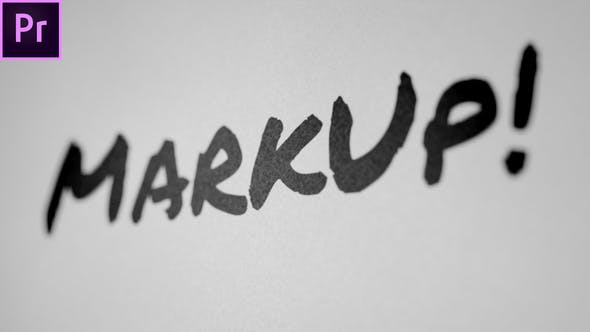
Videohive – MarkUp – Animated Typeface for Premiere – 30833779
هذا محرف متحرك يمكن استخدامه في العديد من مشاريع الفيديو مثل Vlogs و Explainer Videos و Whiteboard Animations و Cartoons و Youtube videos و Invitations و Greeting Cards و Intros وغيرها الكثير.
يتم تحريك الحروف بوتيرة بطيئة بمعدل 60 إطارًا في الثانية ، مما يسمح لك بتغيير سرعة الكتابة من بطيئة جدًا ومفصلة إلى سريعة دون أي خسارة في الجودة.
يعد العمل مع المحرف سهلاً كما هو: كل ما تحتاجه هو كتابة النص الذي تريده في مربع نص ويقوم قالب الرسوم المتحركة بالباقي نيابةً عنك.